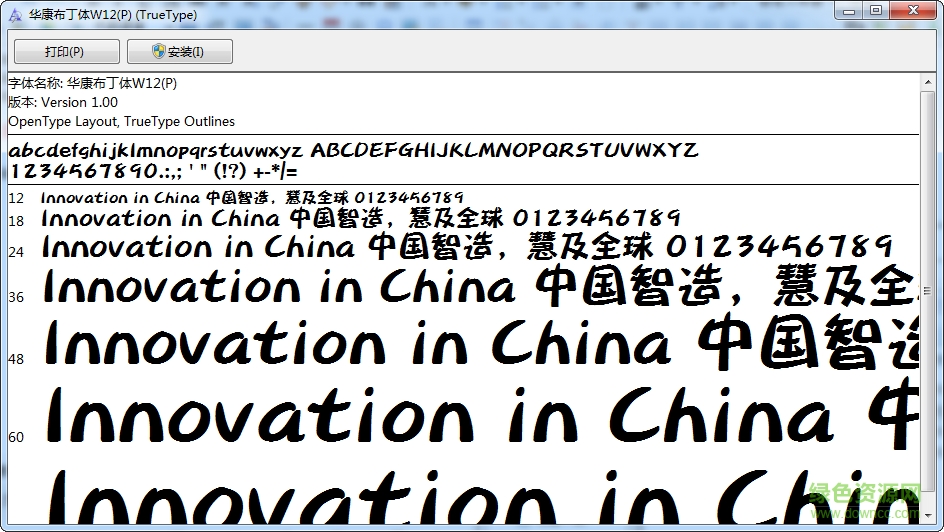
dfpbudingw12字體是一款萌萌噠華康字體,字體圓圓的,就像布丁一樣,十分可愛,可用作各種創(chuàng)意設(shè)計(jì)和特色海報(bào)宣傳方面方面,有興趣的朋友快來(lái)綠色資源網(wǎng)下載吧!
本款dfbudingw12字體是華康布丁體簡(jiǎn)w12,正如字體名字一樣,這款字體效果有點(diǎn)像布丁哦,也就是用于卡通方面的設(shè)計(jì)是非常合適的啦。